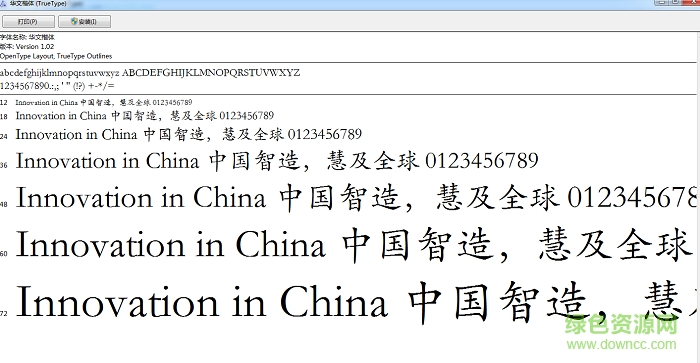
stkaiti-sc-regular字体
stkaiti-sc-regular字体是一款常规体的华文楷体字体,布白匀称,笔形柔和,一笔一画都非常规矩清楚,用在正文、说明等内容上都可以!
小楷字体介绍
小楷,顾名思义,是楷书之小者,创始于三国魏时的钟繇。他原是位隶书最杰出的权威大家,所作楷书的笔意,亦脱胎于汉隶,笔势恍如飞鸿戏海,极生动之致。惟结体宽扁,横画长而直画短,仍存隶分的遗意,然已备尽楷法,实为正书之祖。到了东晋王羲之,将小楷书法更加以悉心钻研,使之达到了尽善尽美的境界,亦奠立了中国小楷书法优美的欣赏标准。